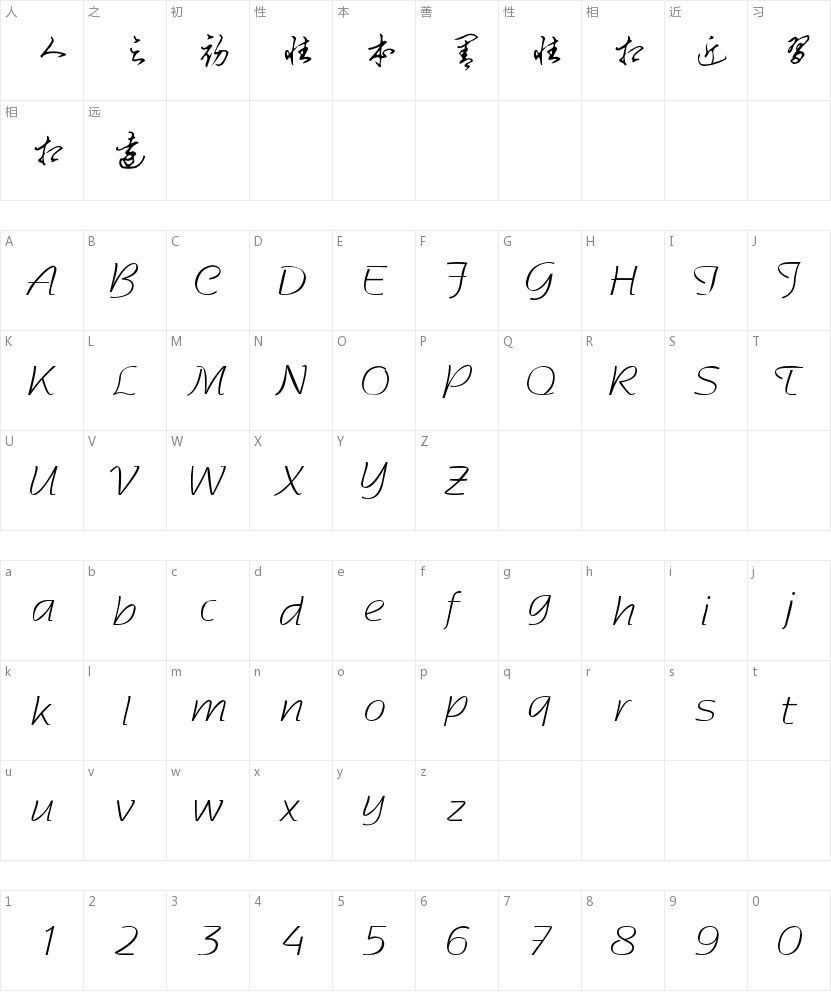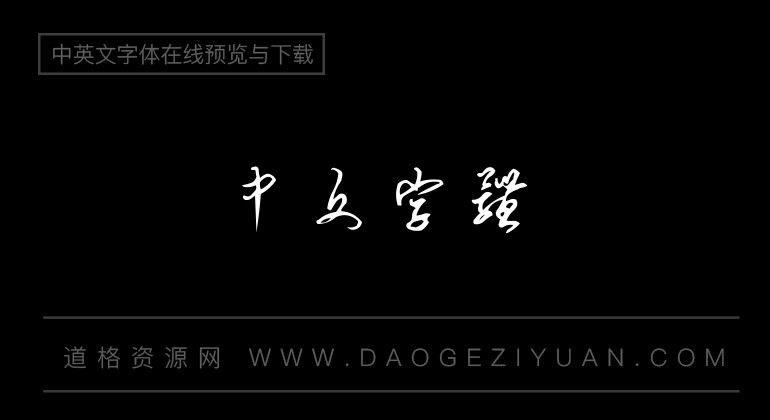
博洋草书7000是一款由博洋文化出品的中文字体,它是一款经典的中文草书字体,它结合了草书的传统美感和现代技术,拥有清新明快的字形,细腻柔和的笔画,整体风格细腻大方,符合当今设计的流行趋势,是一款非常适合用于印刷品、网页设计、商标设计等场景的中文字体。文件名:BoYangCaoShu7000-1.ttf
博洋草书7000是一款非常不错的手写艺术字体,具有很好的视觉感,适合于文化类的宣传设计、商业类品牌的广告和产品包装设计以及个性化文字排版等较多场景。